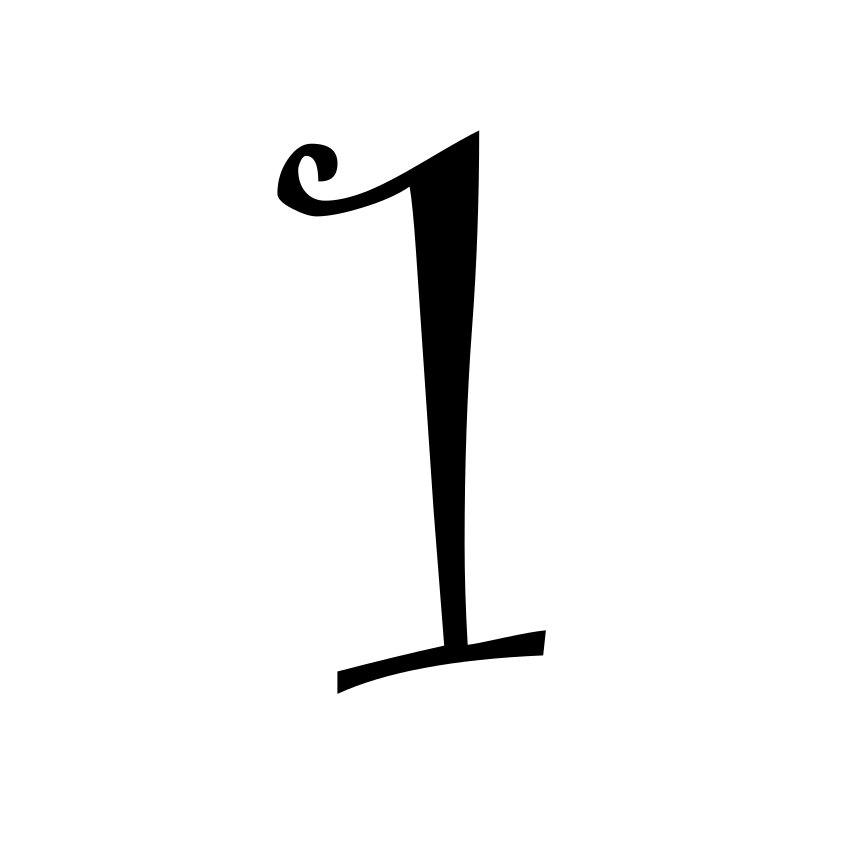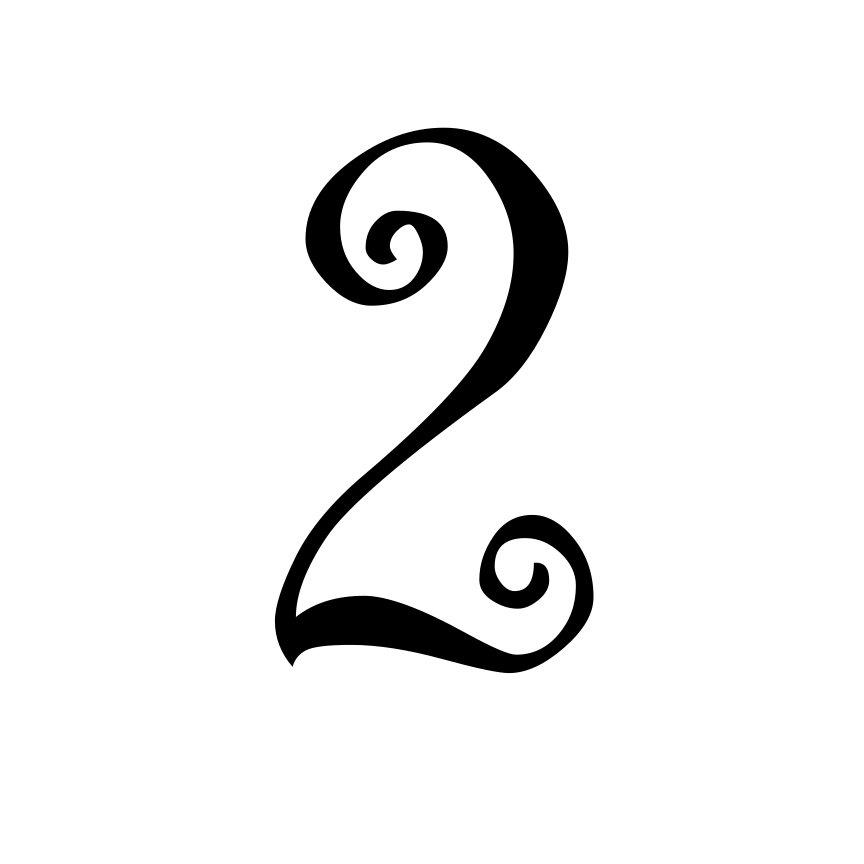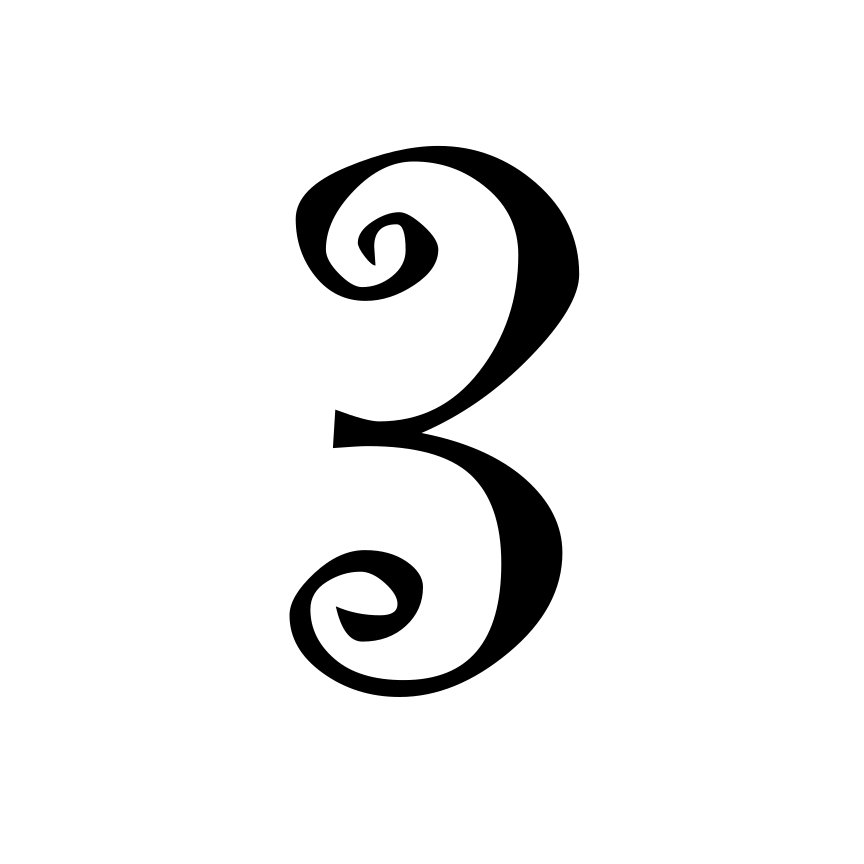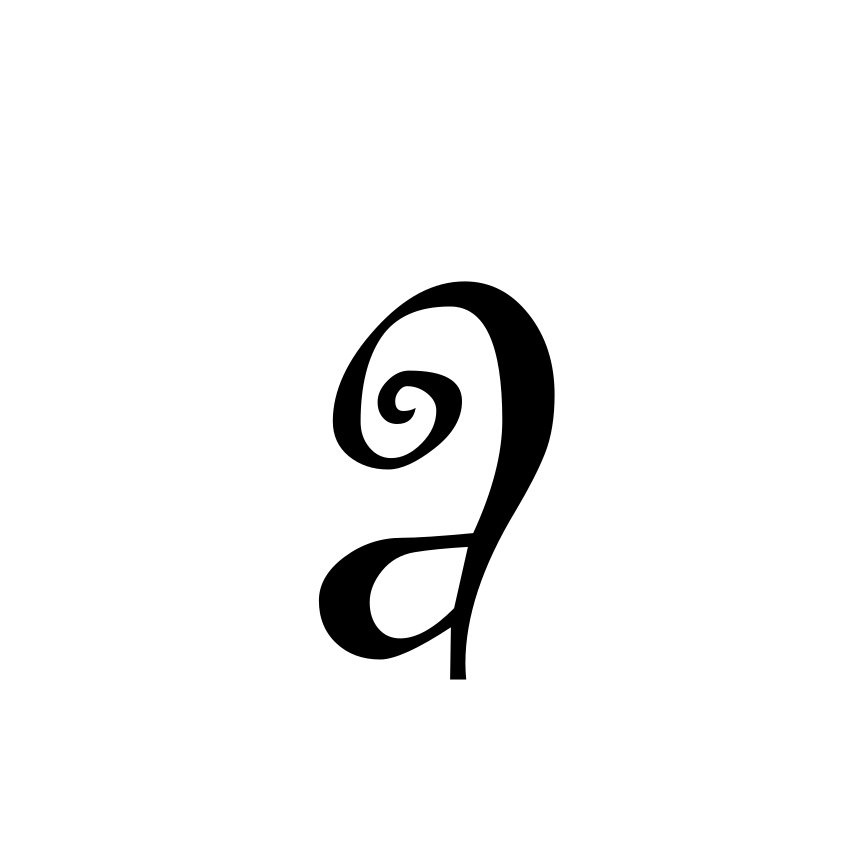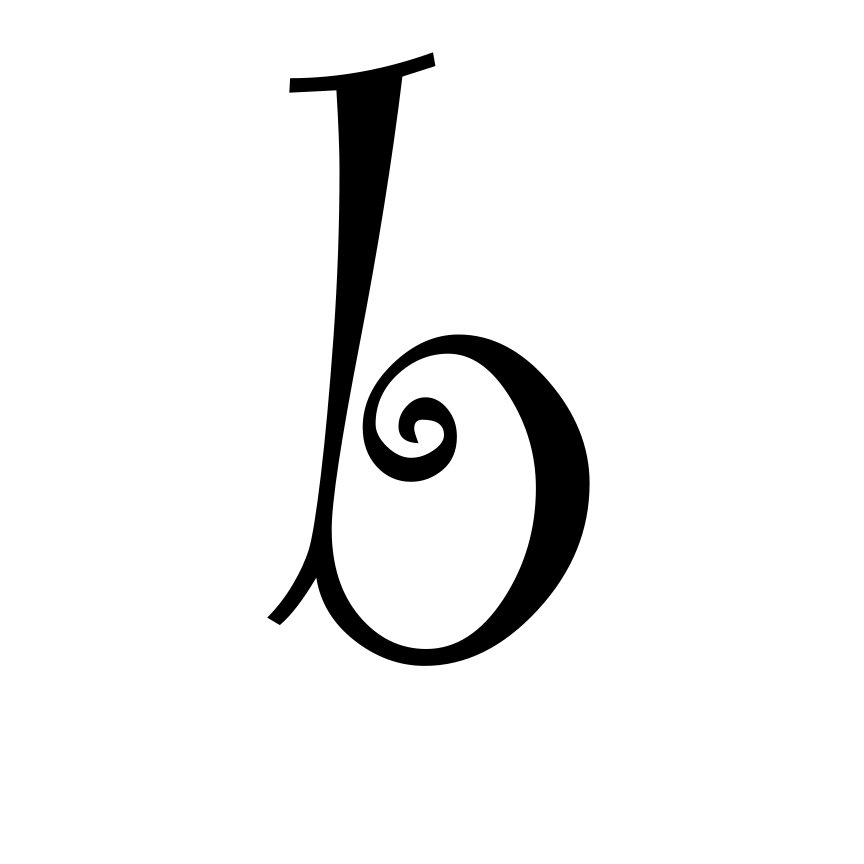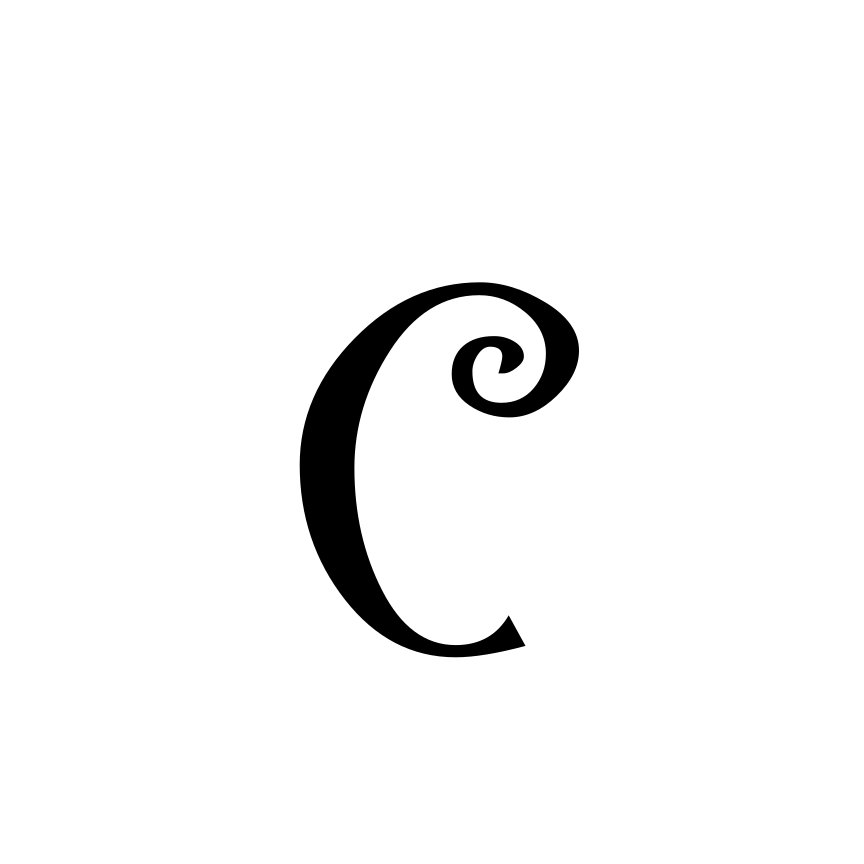
Curly Doodle Monogramm Schriftart – Verspieltes Wirbel-Alphabet mit Grossbuchstaben, Kleinbuchstaben, Zahlen und Satzzeichen | Cricut-kompatibel
• Die Curly Doodle Monogramm Schriftart ist ein dekoratives Alphabet mit verspielten Schwüngen und handgezeichnet wirkenden Locken. Die fliessenden Formen verleihen jedem Buchstaben eine kreative und leichte Optik, während die Schrift gleichzeitig klar und gut lesbar bleibt.
• Diese Monogramm-Schrift enthält Grossbuchstaben, Kleinbuchstaben, Zahlen sowie Satzzeichen, sodass sich Namen, Initialen und personalisierte Texte in einem einheitlichen, geschwungenen Stil gestalten lassen.
• Die weichen Wirbel-Details geben Monogramm-Designs und dekorativen Schriftzügen eine besondere, verspielte Note, während alle Zeichen harmonisch und ausgewogen gestaltet sind. Dadurch eignet sich die Schrift ideal für viele kreative Bastel- und Designprojekte.